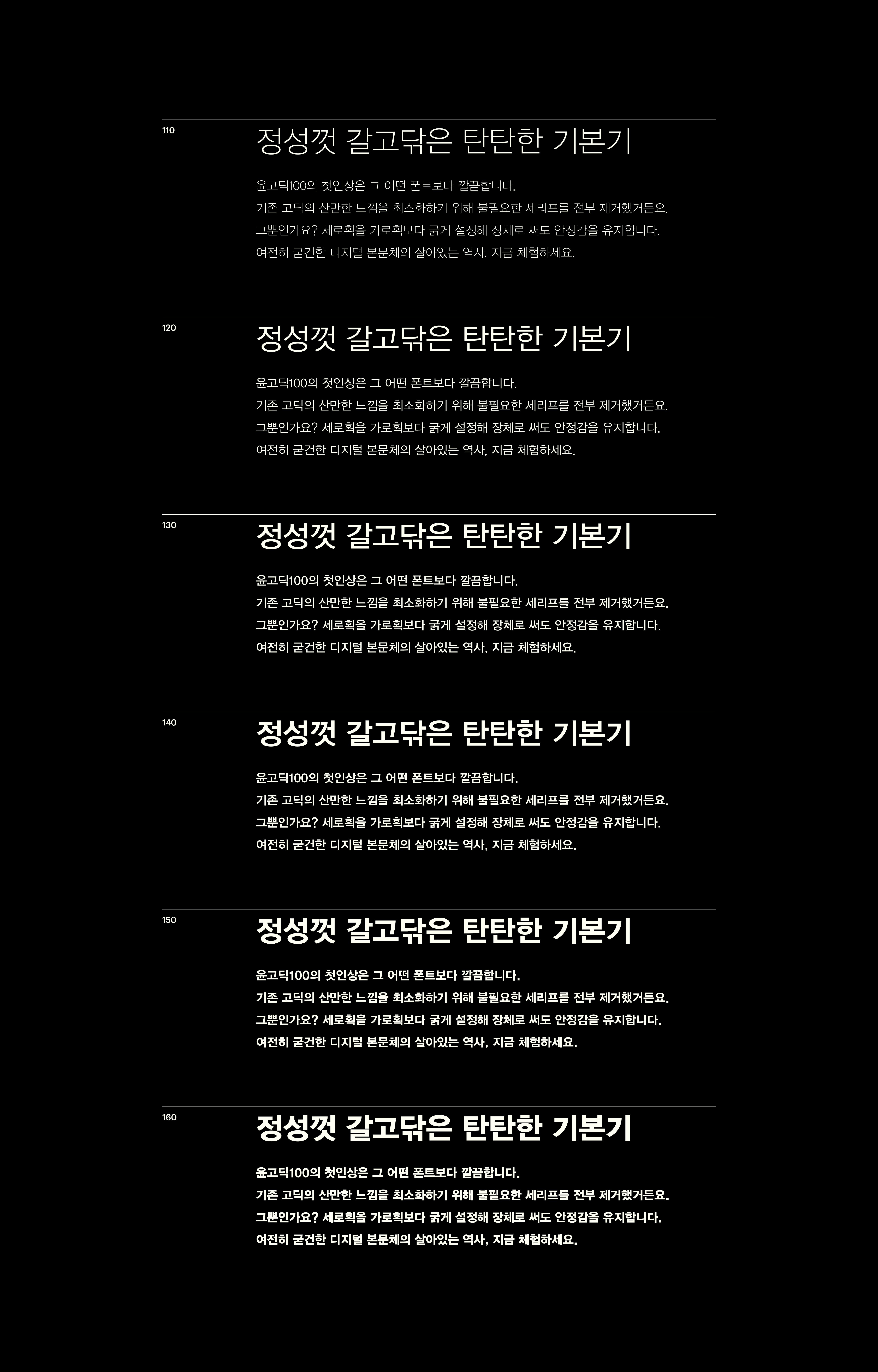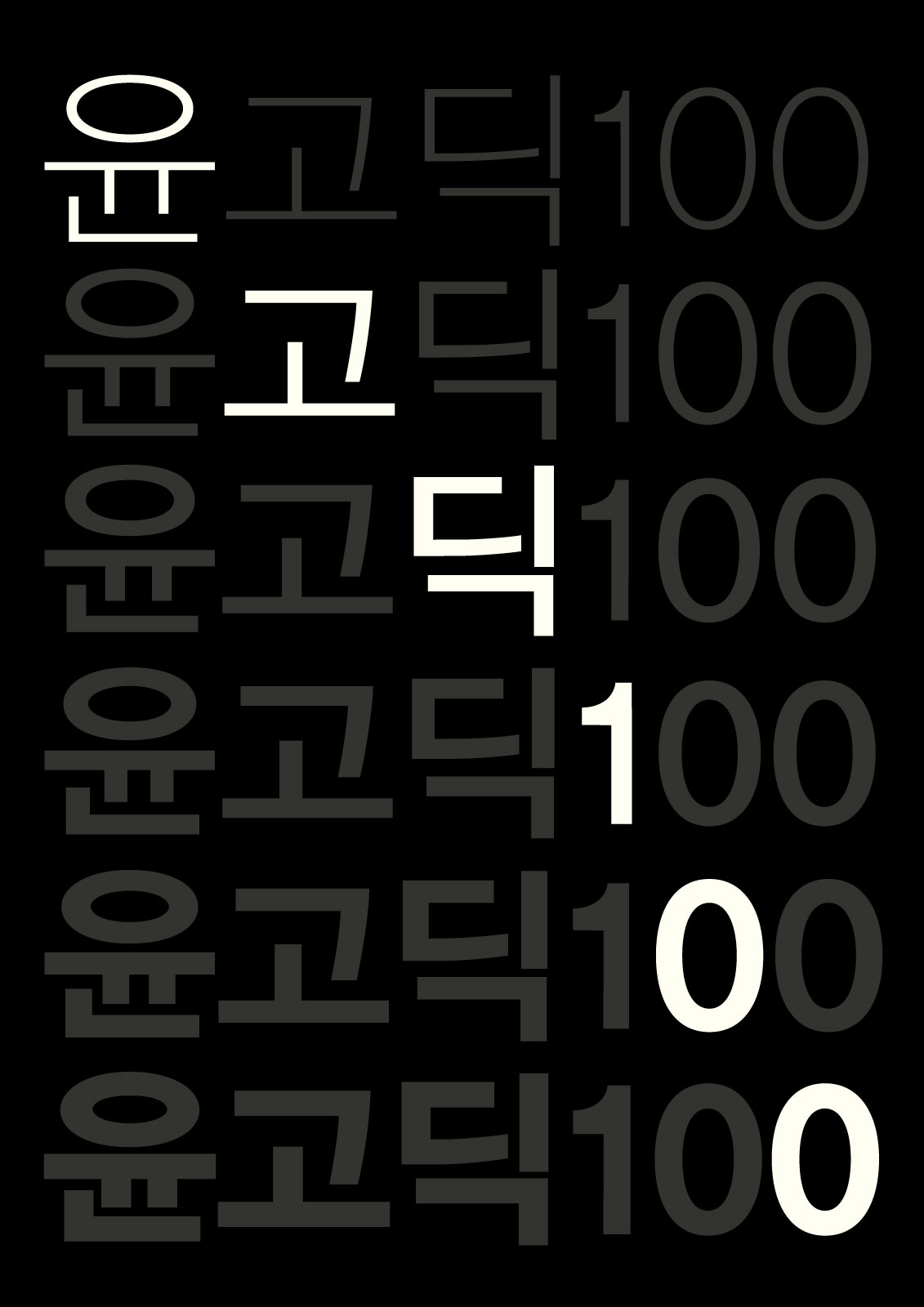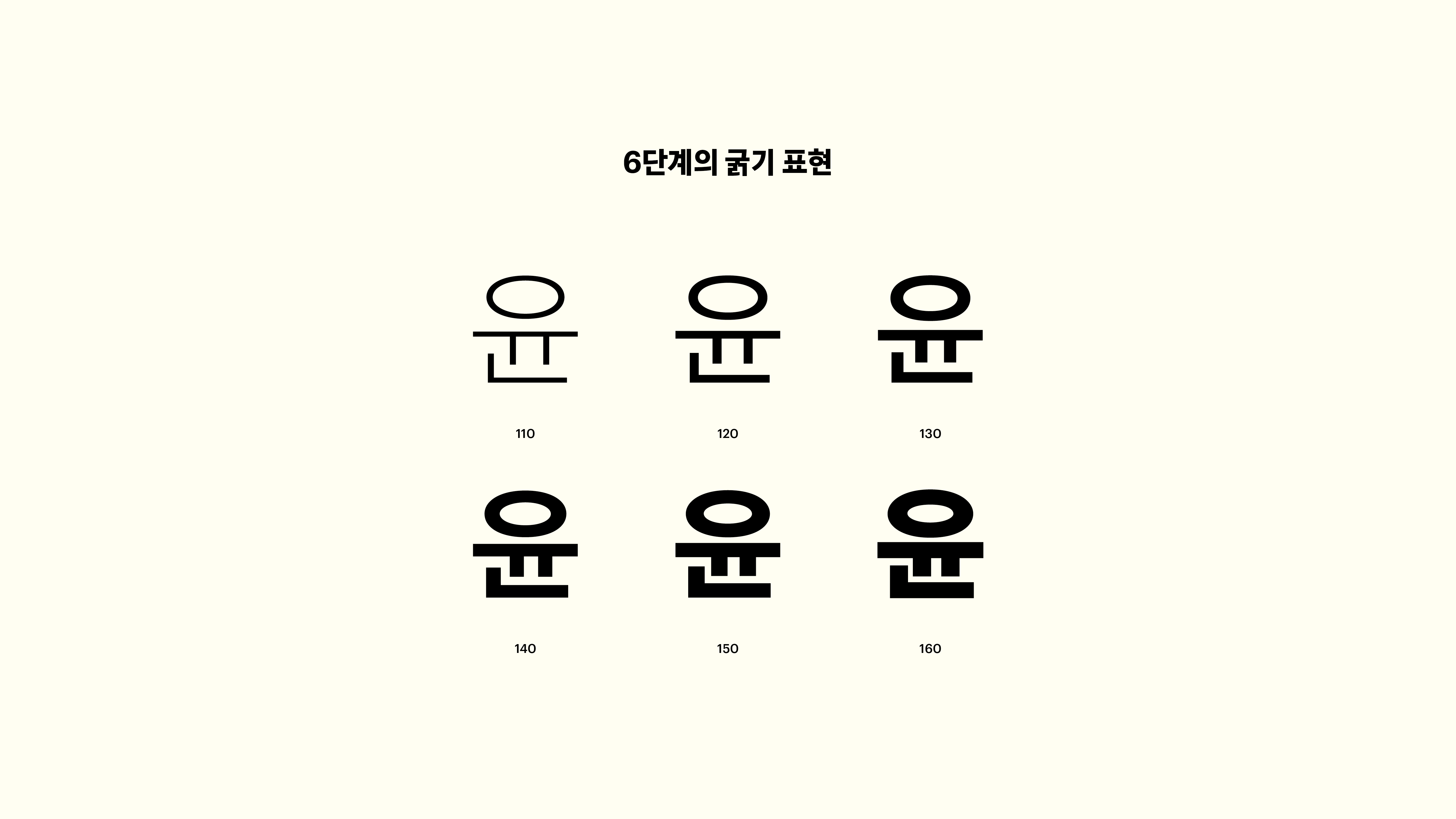
윤고딕 100
1990-1994
Yoon 윤고딕 100
윤고딕100의 첫인상은 그 어떤 폰트보다 깔끔합니다. 기존 고딕의 산만한 느낌을 최소화하기 위해 불필요한 세리프를 전부 제거했거든요. 그뿐인가요? 가로획과 세로획의 굵기 대비가 적절하므로 장체로 써도 삐침이 벌어지지 않습니다. 너도, 나도 즐겨 쓴다 했더니, 다 그만한 이유가 있었지 뭐예요!